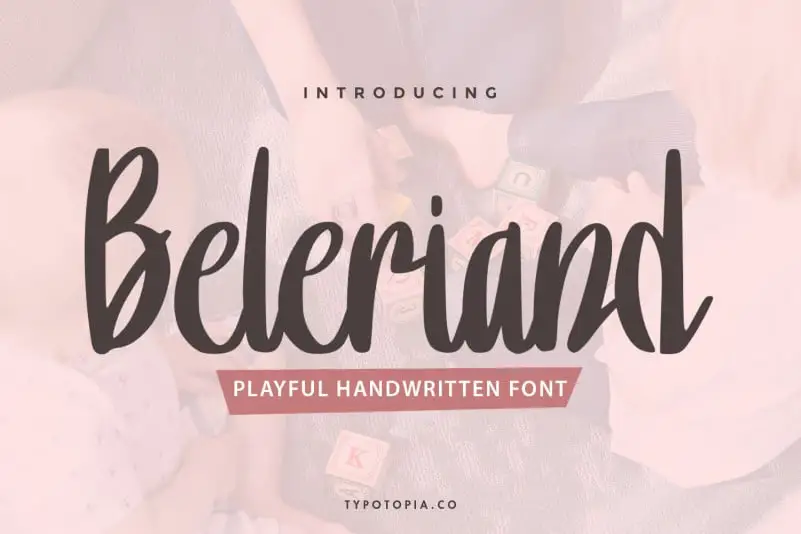
Beleriand Playful Handwriten Font – Download Grátis
Introduzimos Beleriand Handwriten Font, uma tipografia escrita a mão com estilo divertido. Especialmente projetada para aplicação nos mais variados formatos e ambientes de mídia, este tipo de fonte é perfeita tanto para criar logos como para design de estantes, revistas, menus, capas de livros, cartões de visita, convites e até mesmo etiquetas para produtos. Beleriand Handwriten Font também se encaixa bem em embalagens de produto, materiais publicitários e cards de negócios. Seja você designer gráfico, escritor ou editor de conteúdo, está na hora de adicionar um pouco mais de vida à sua arte digital. A Beleriand Handwriten Font oferece a oportunidade de trazer uma pitada de diversão a qualquer projeto visual que você estiver trabalhando. Suave e encantadora, esta fonte escrita a mão é o elemento perfeito para transformar qualquer layout em um design impecável. Ideal para quem busca um toque especial no seu trabalho gráfico, Beleriand Handwriten Font é uma fonte de texto perfeita que combina elegância e criatividade. Não importa o formato ou a plataforma do seu projeto – seja ele digital ou impresso, este tipo de fonte vai manter sua identidade única, tornando seu trabalho ainda mais especial.